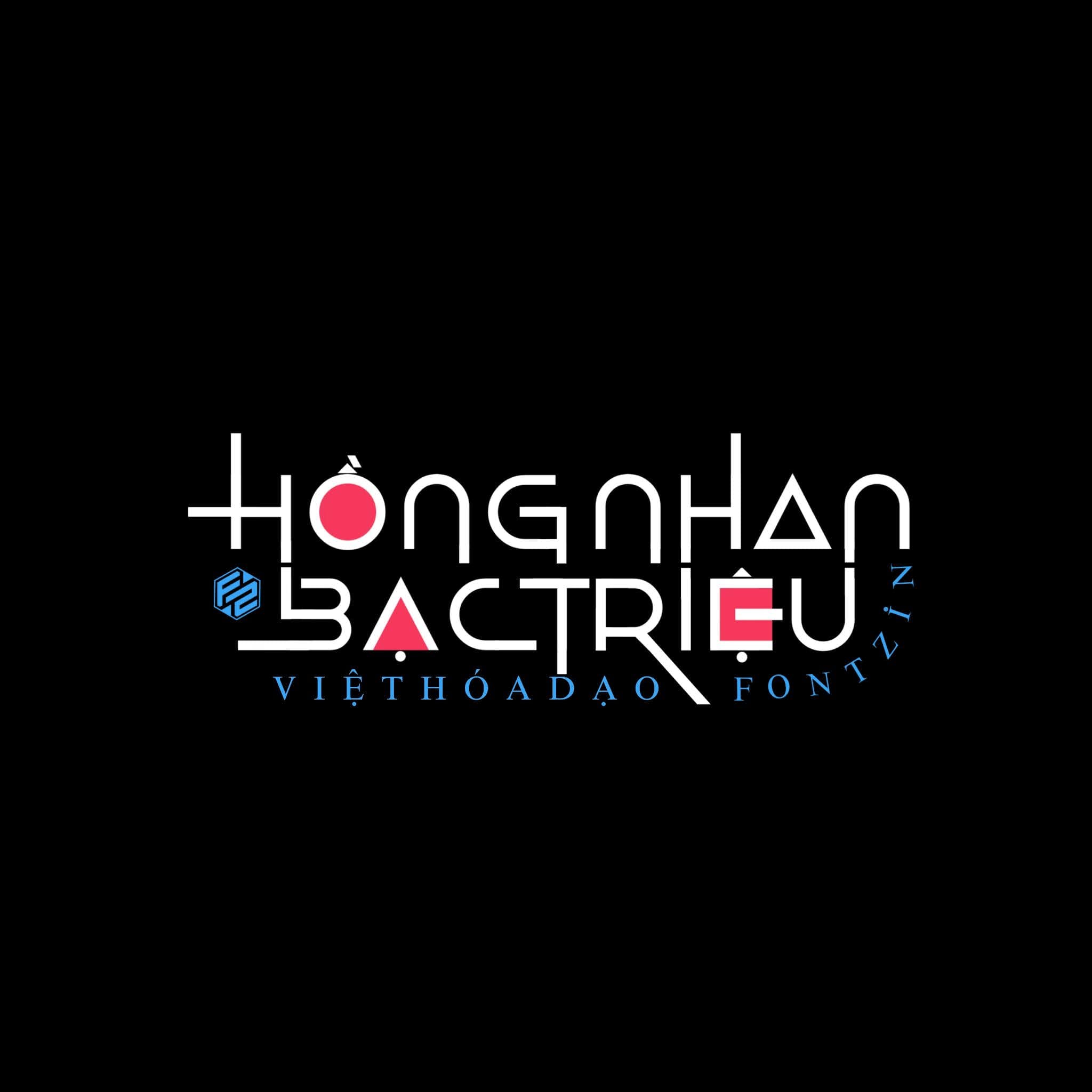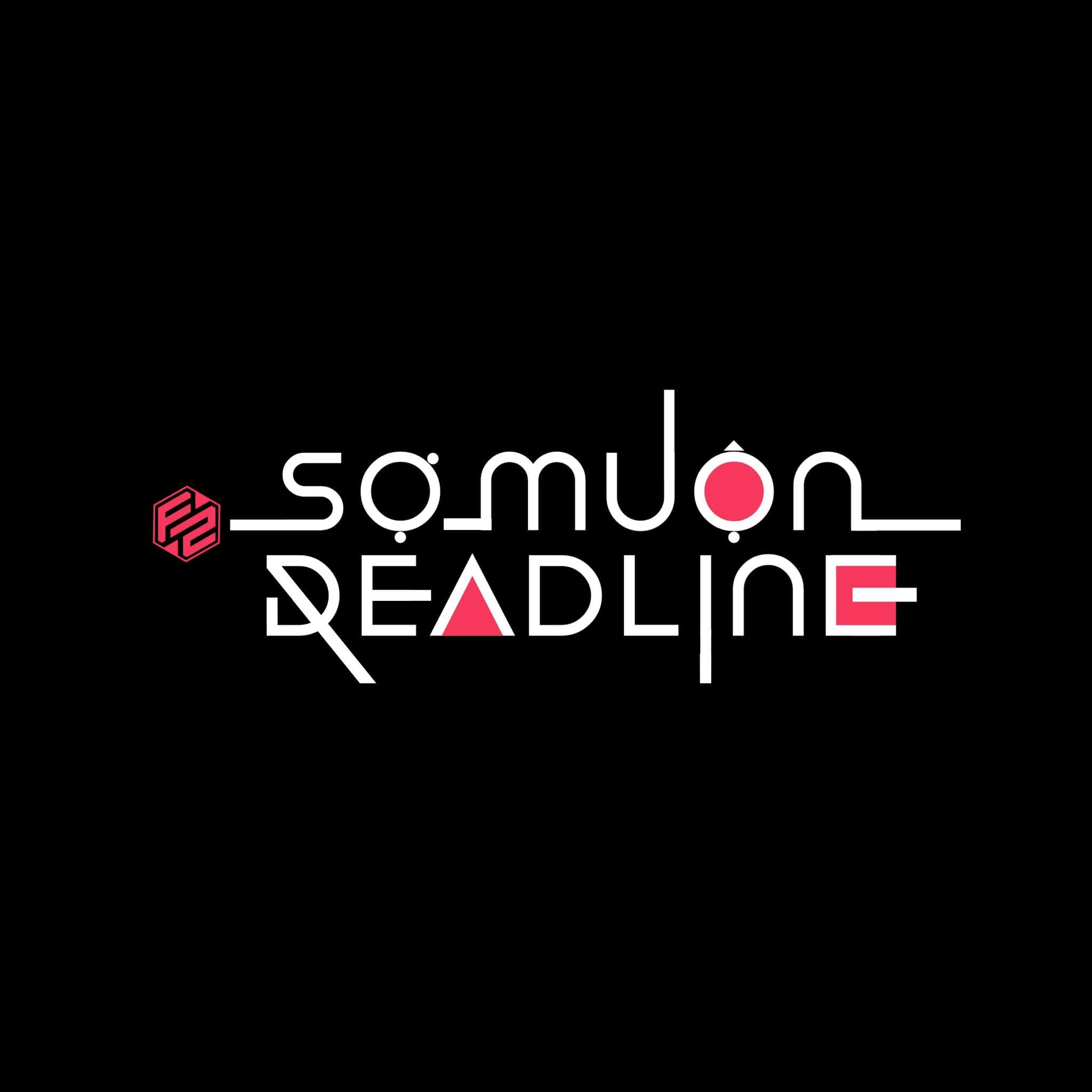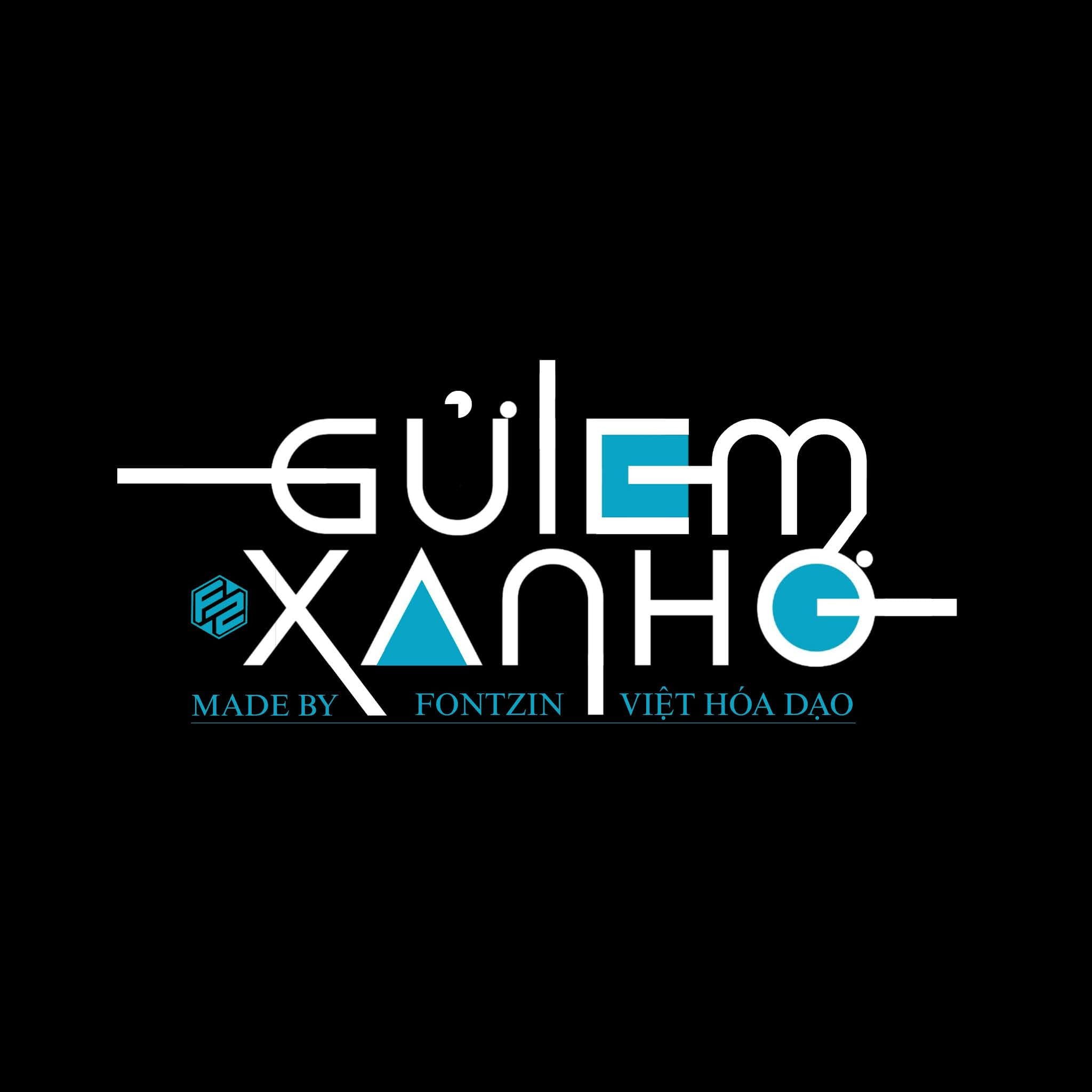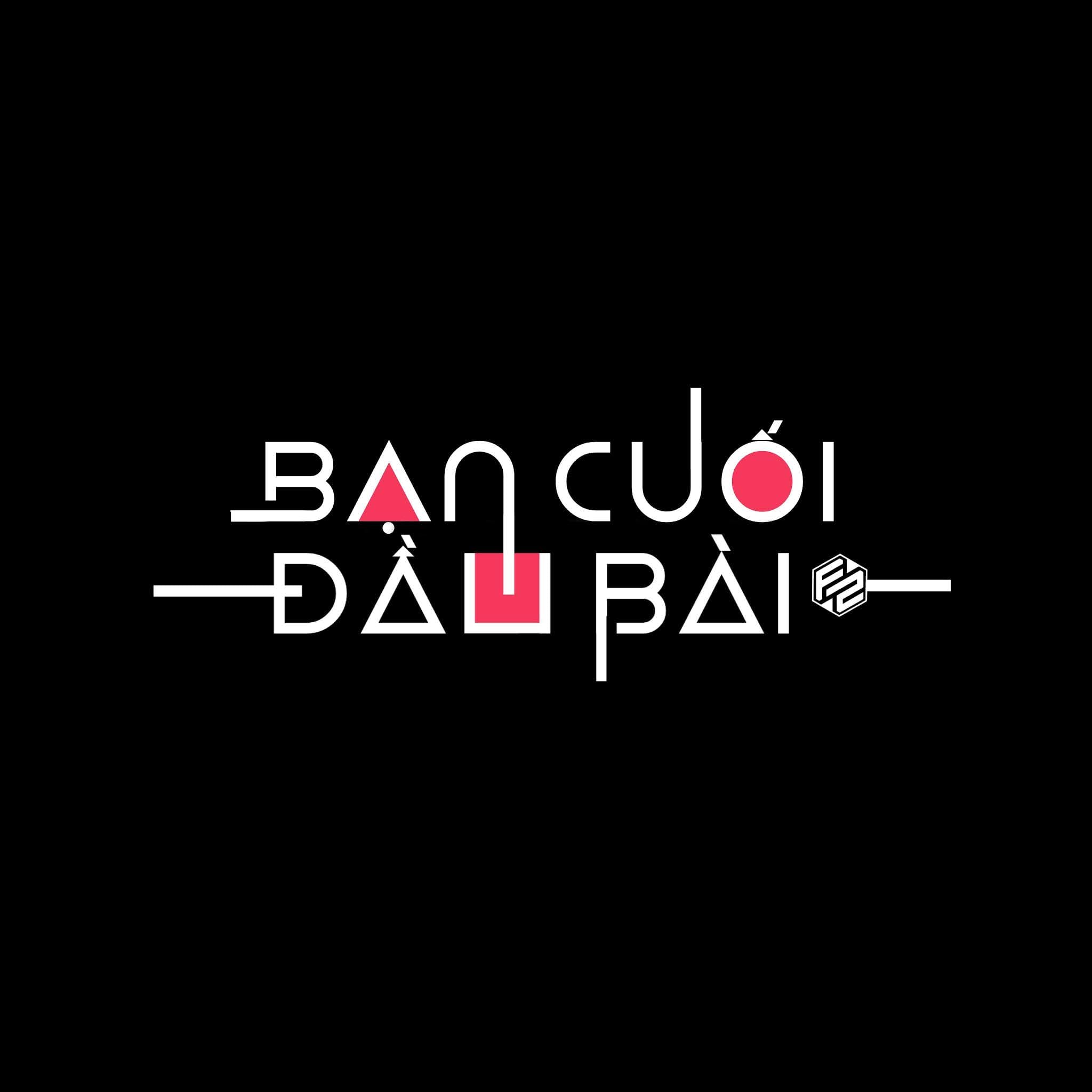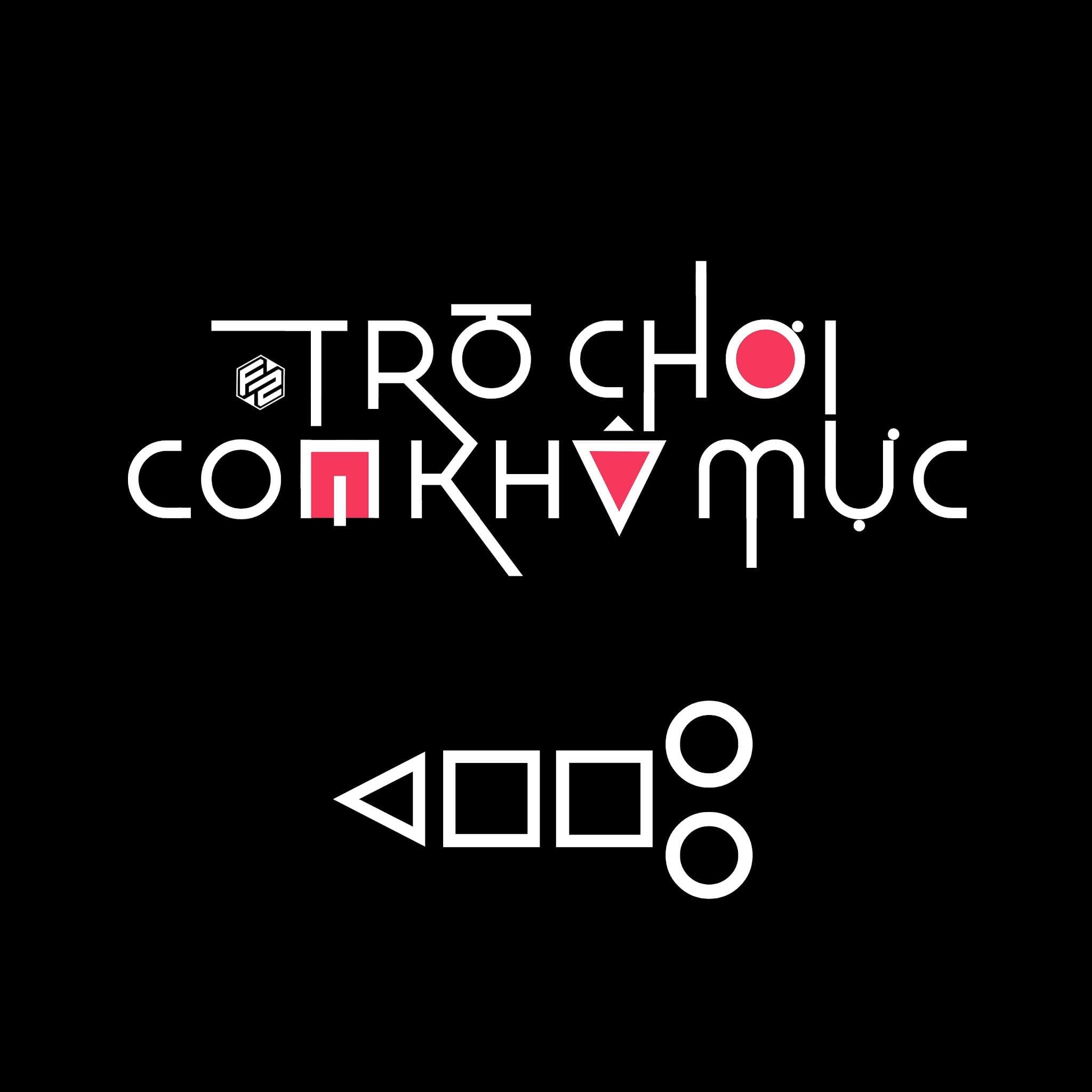
Squid Game (Trò chơi con mực) tựa game đang gây sốt trong thời gian qua. Tuy nhiên ở đây mình không giới thiệu phim mà giới thiệu font chữ Squid Game Việt Hóa, font gốc là Slug Half đây là font khá giống với trên poster phim này sử dụng.